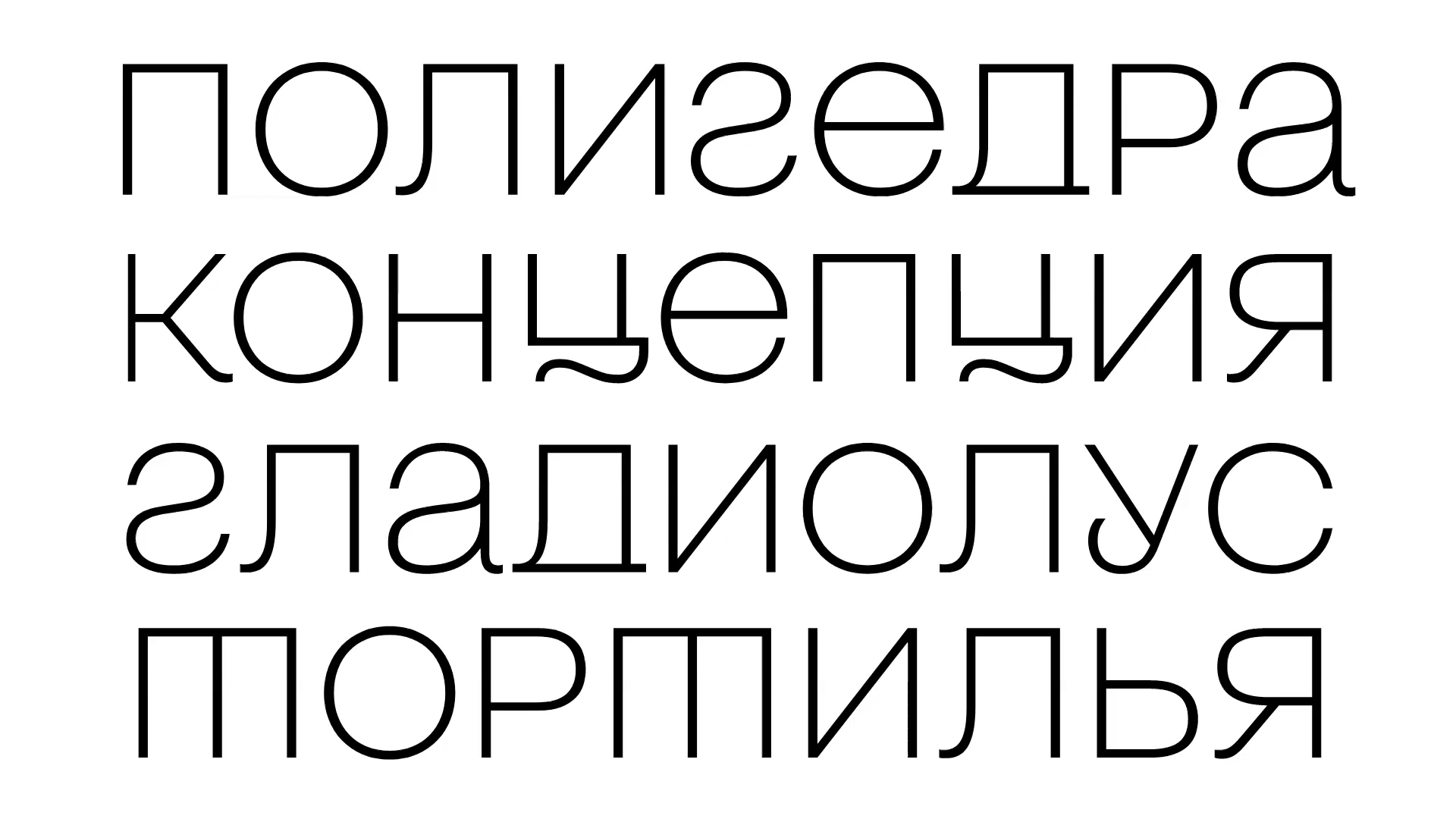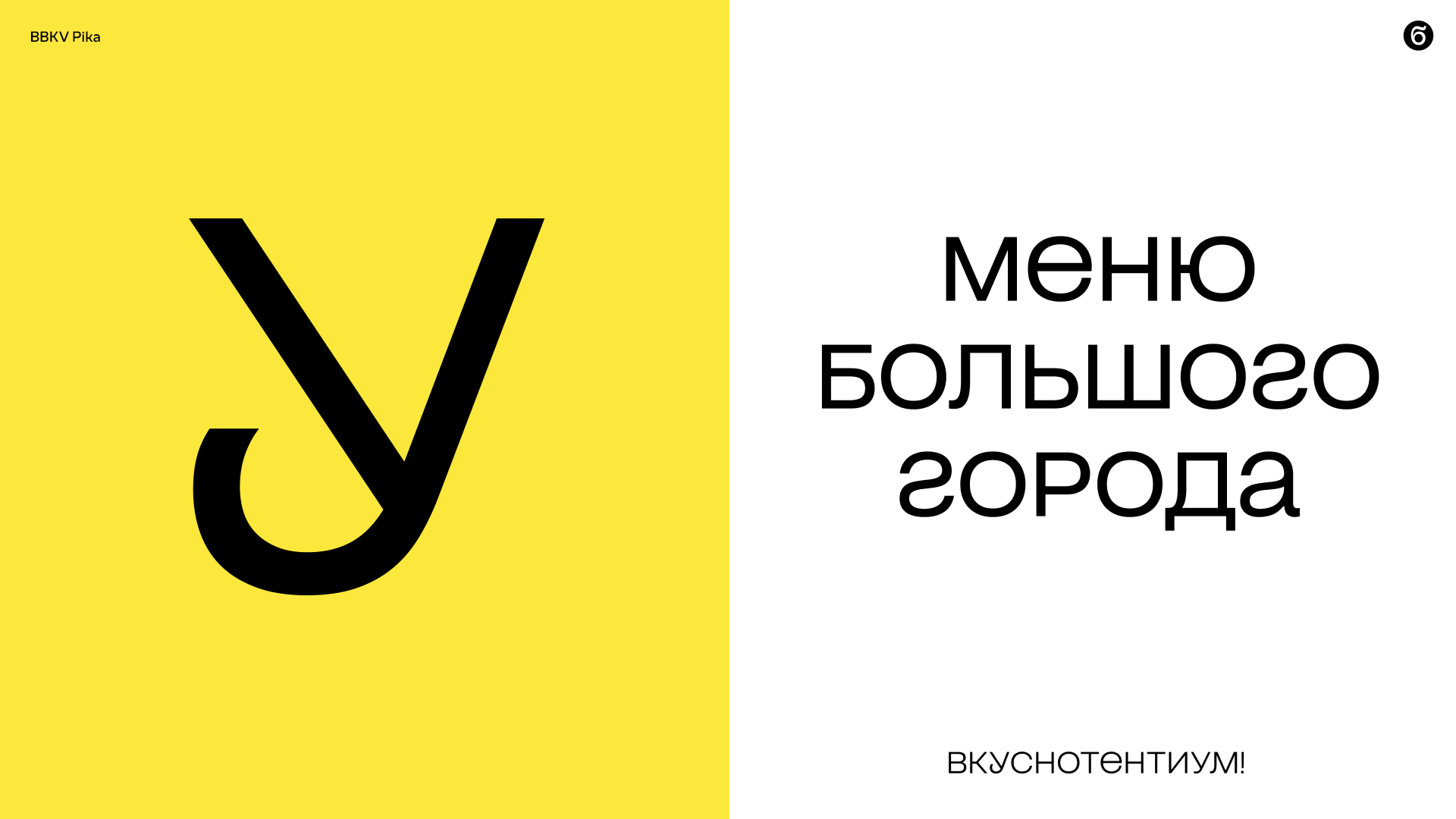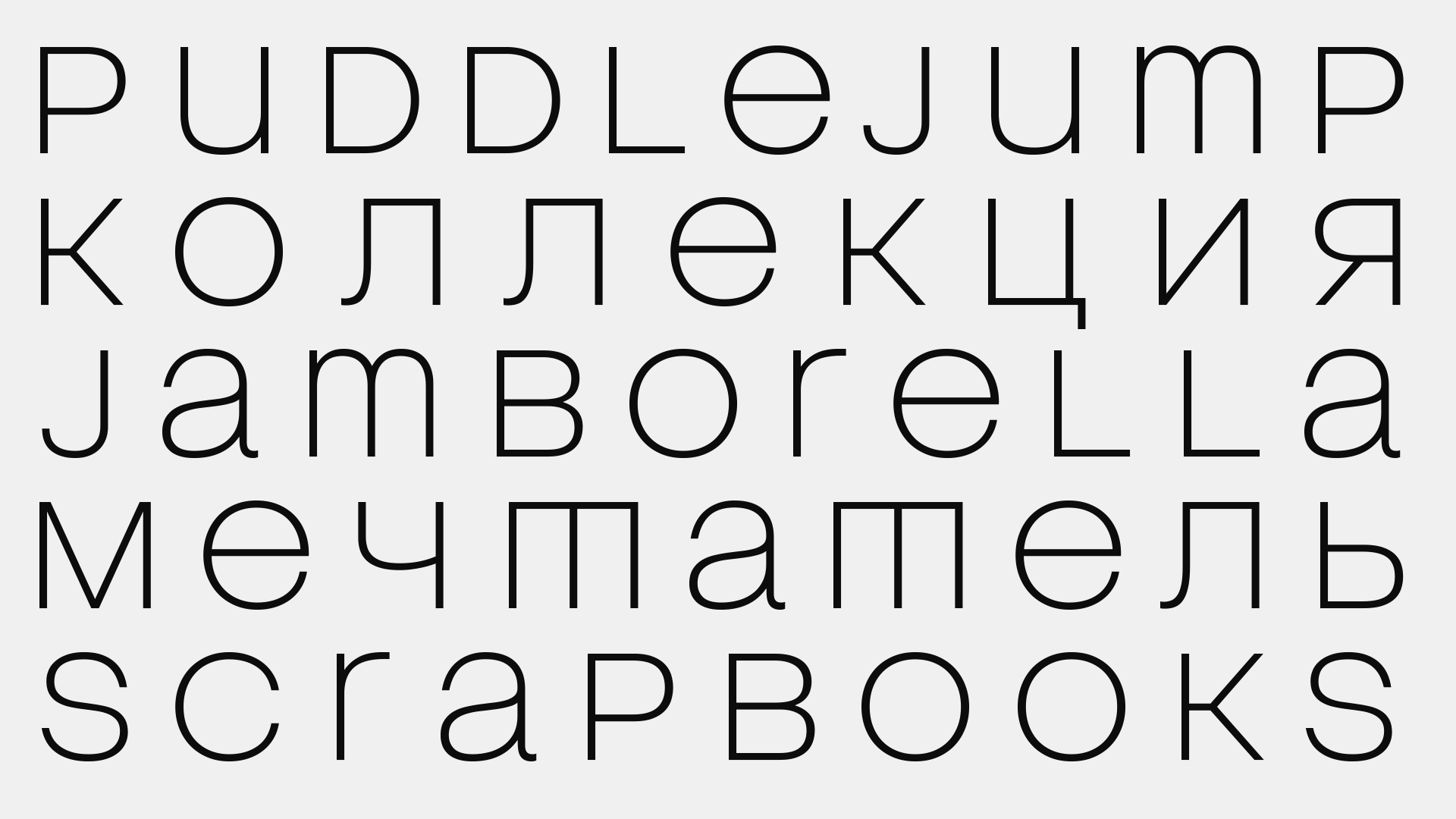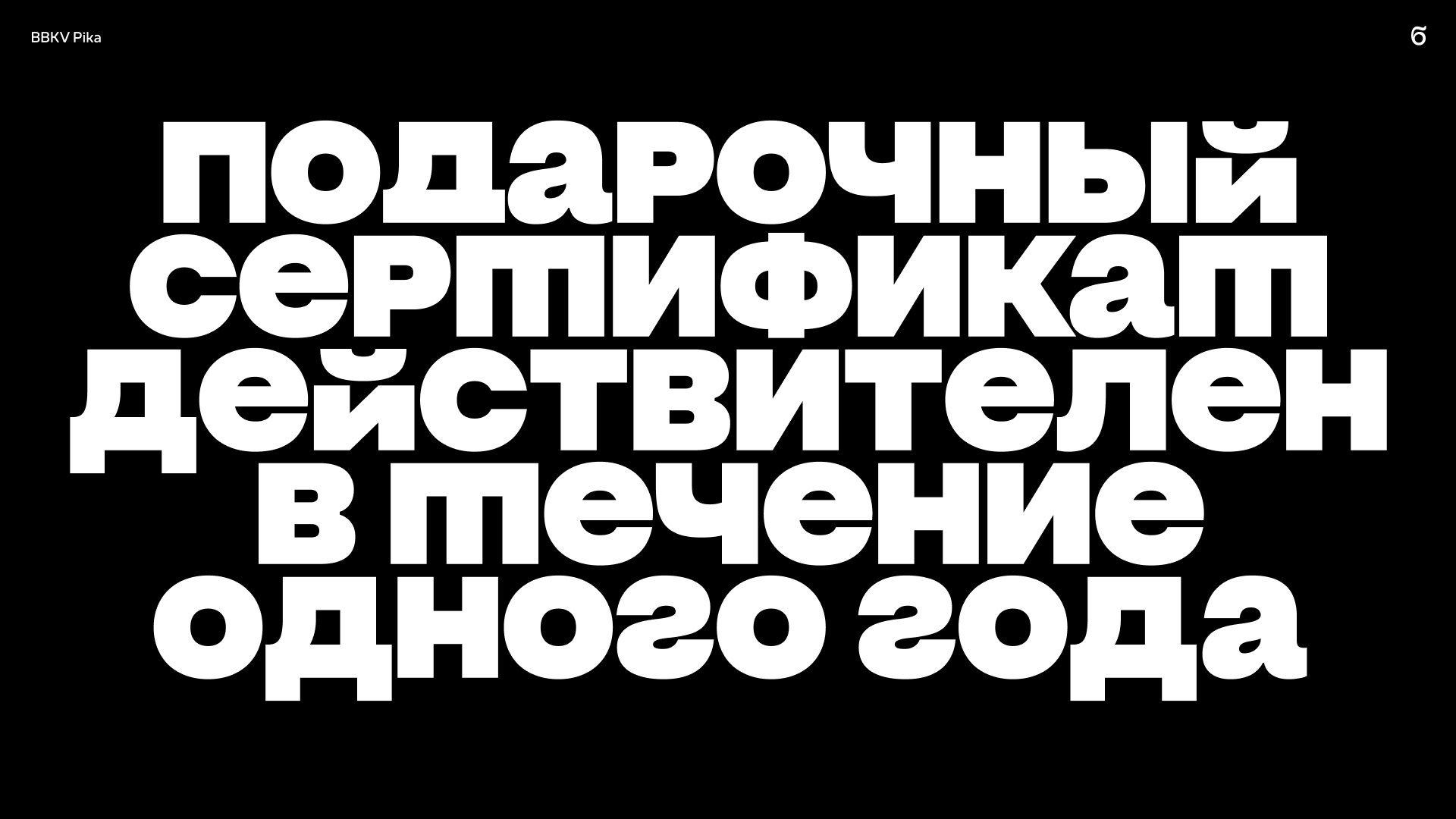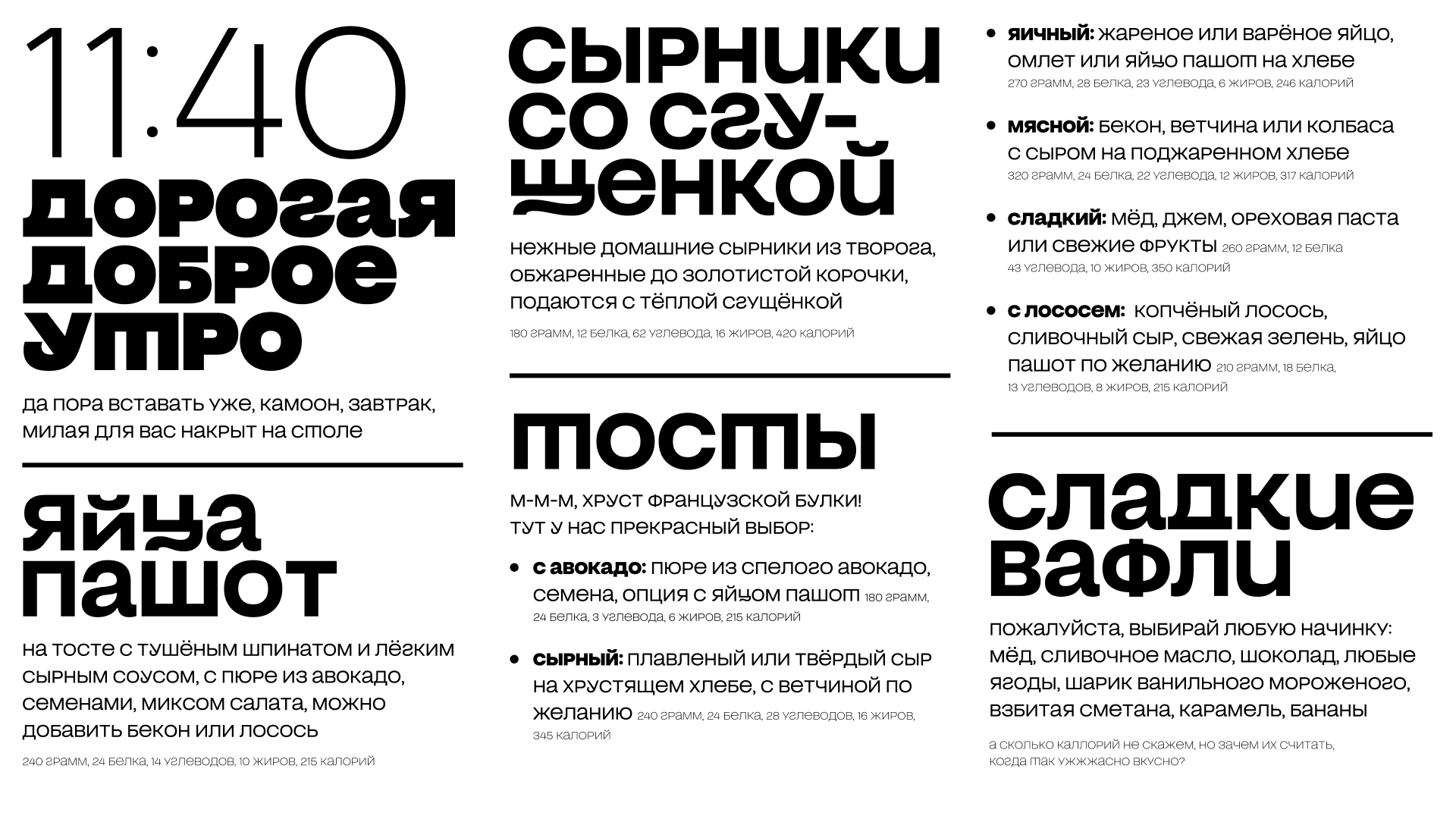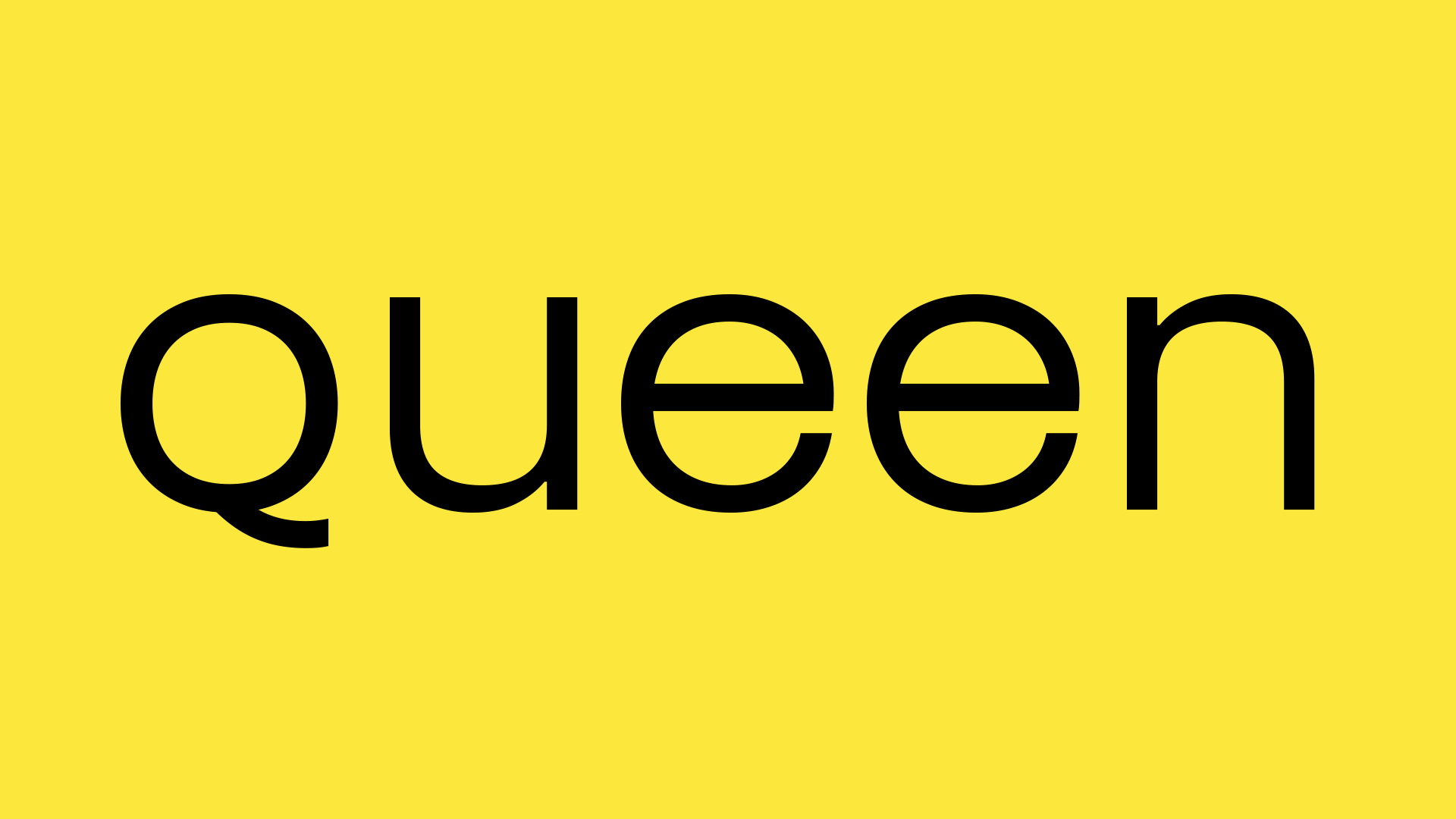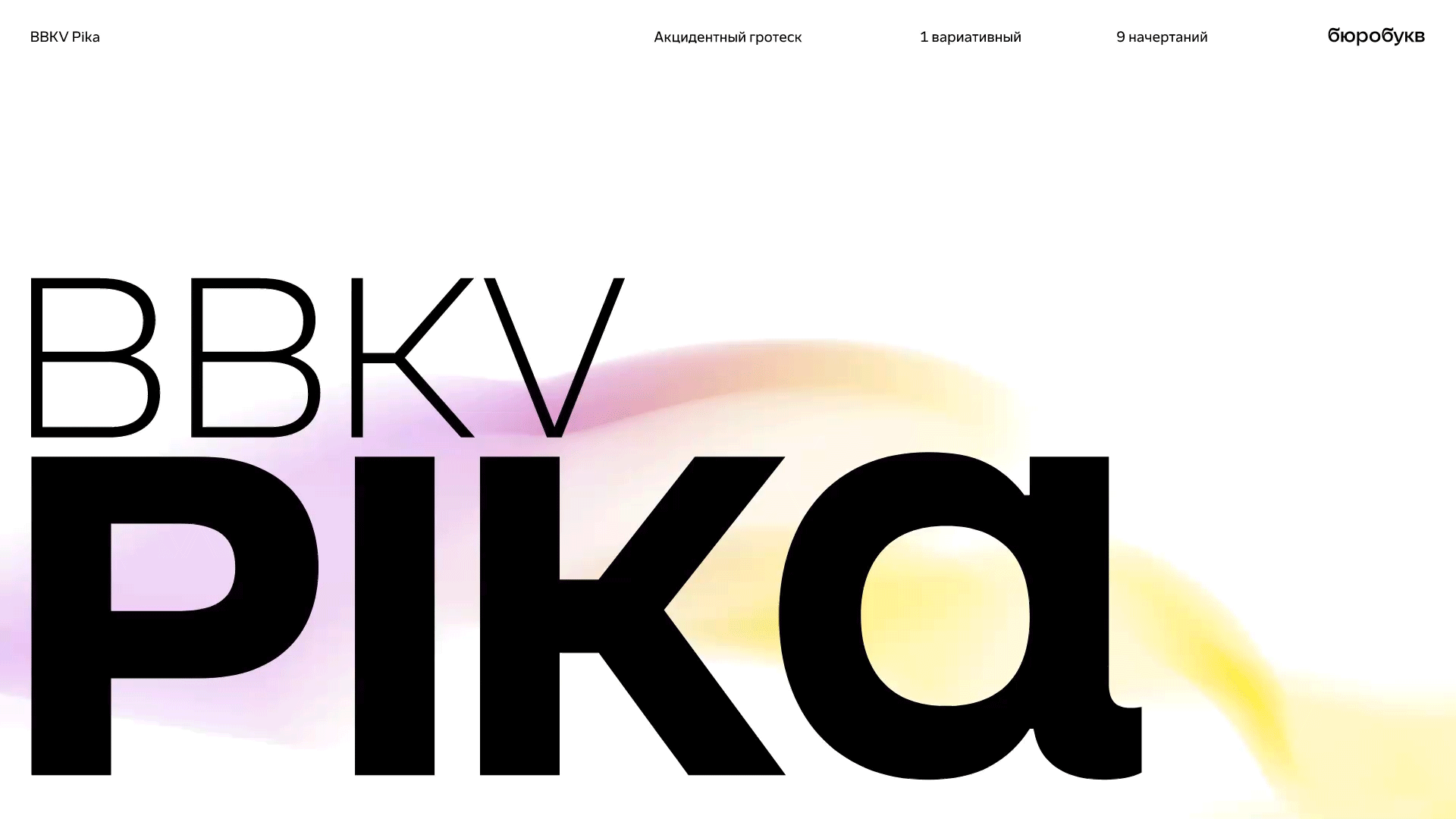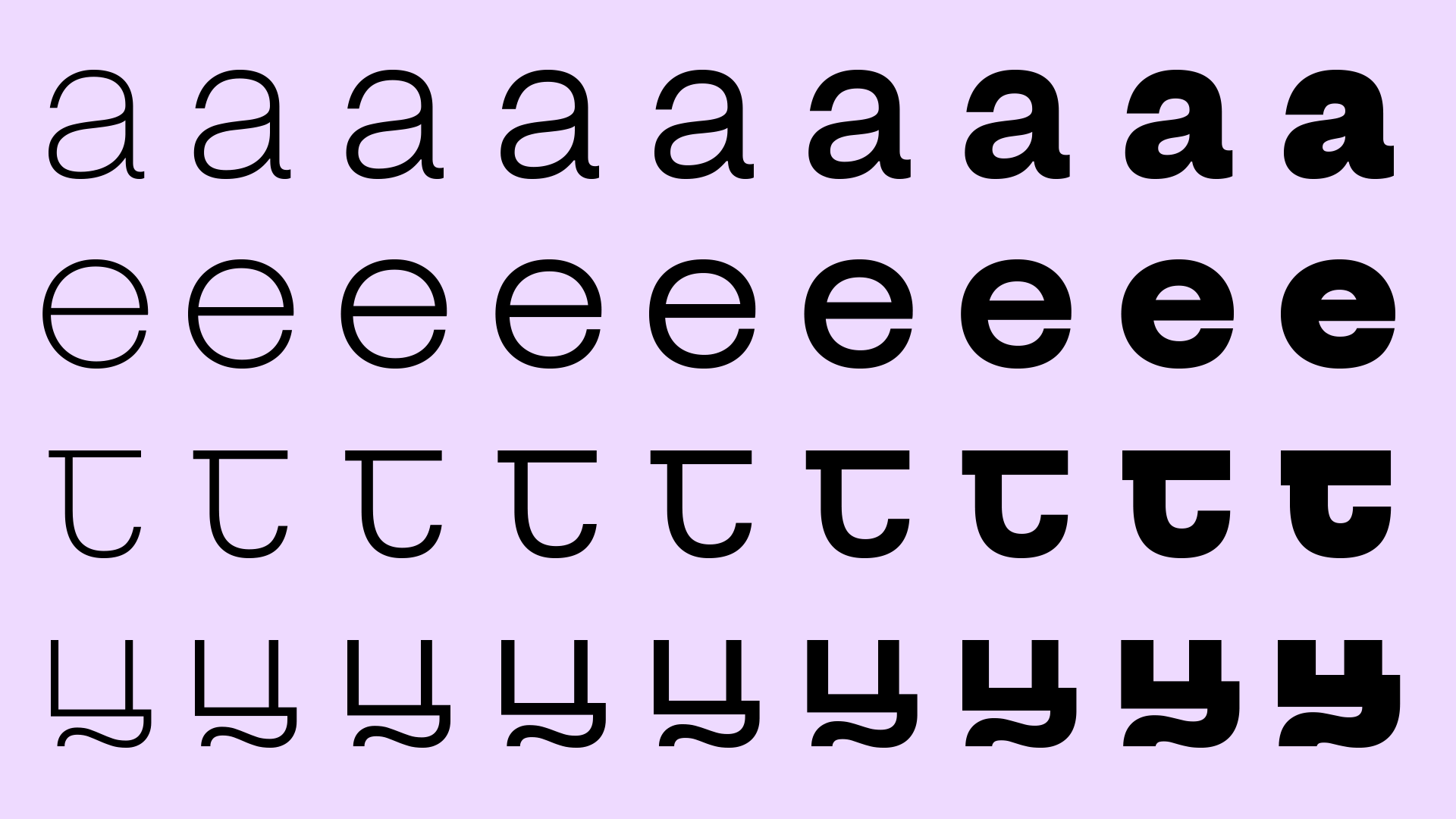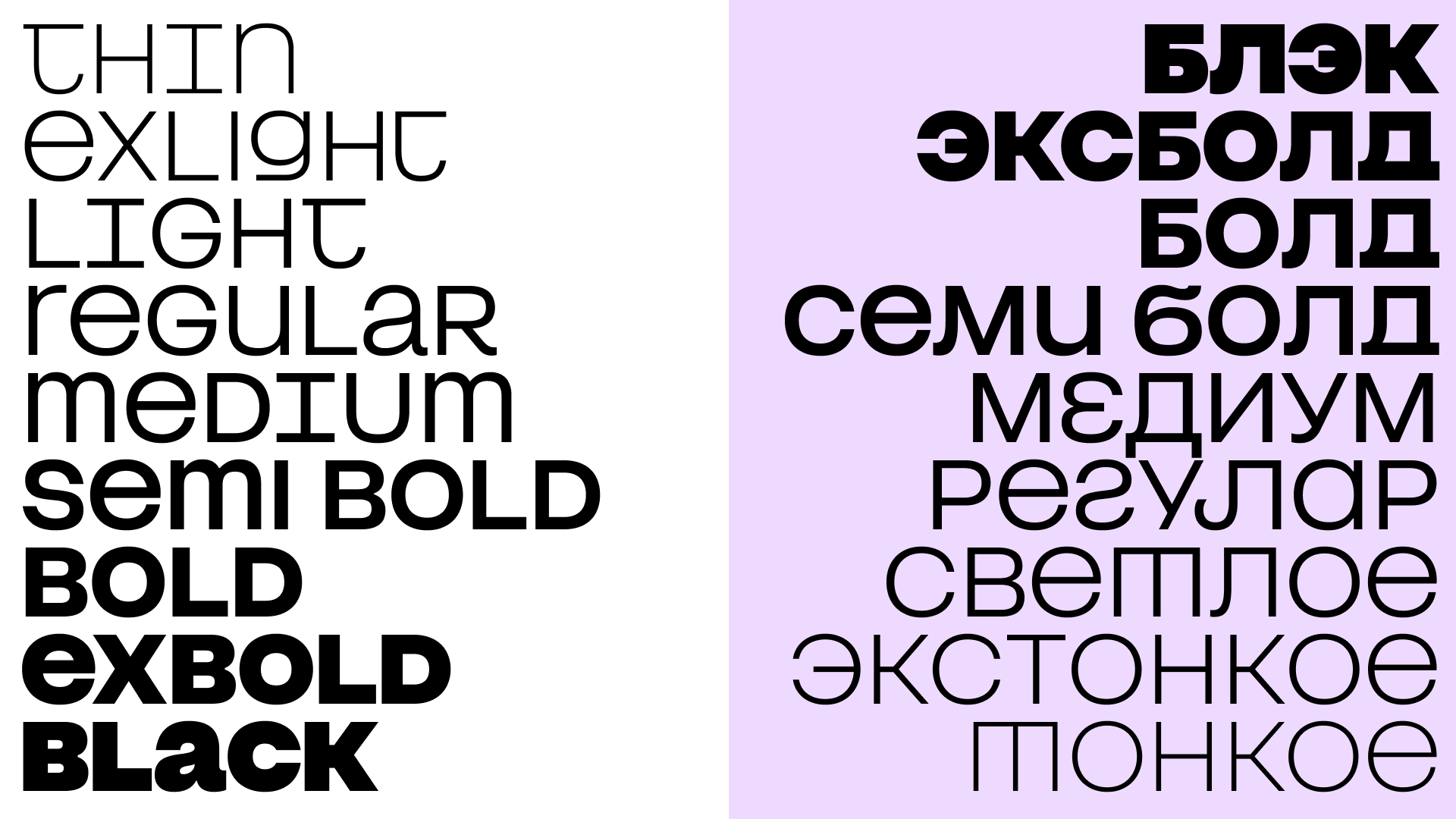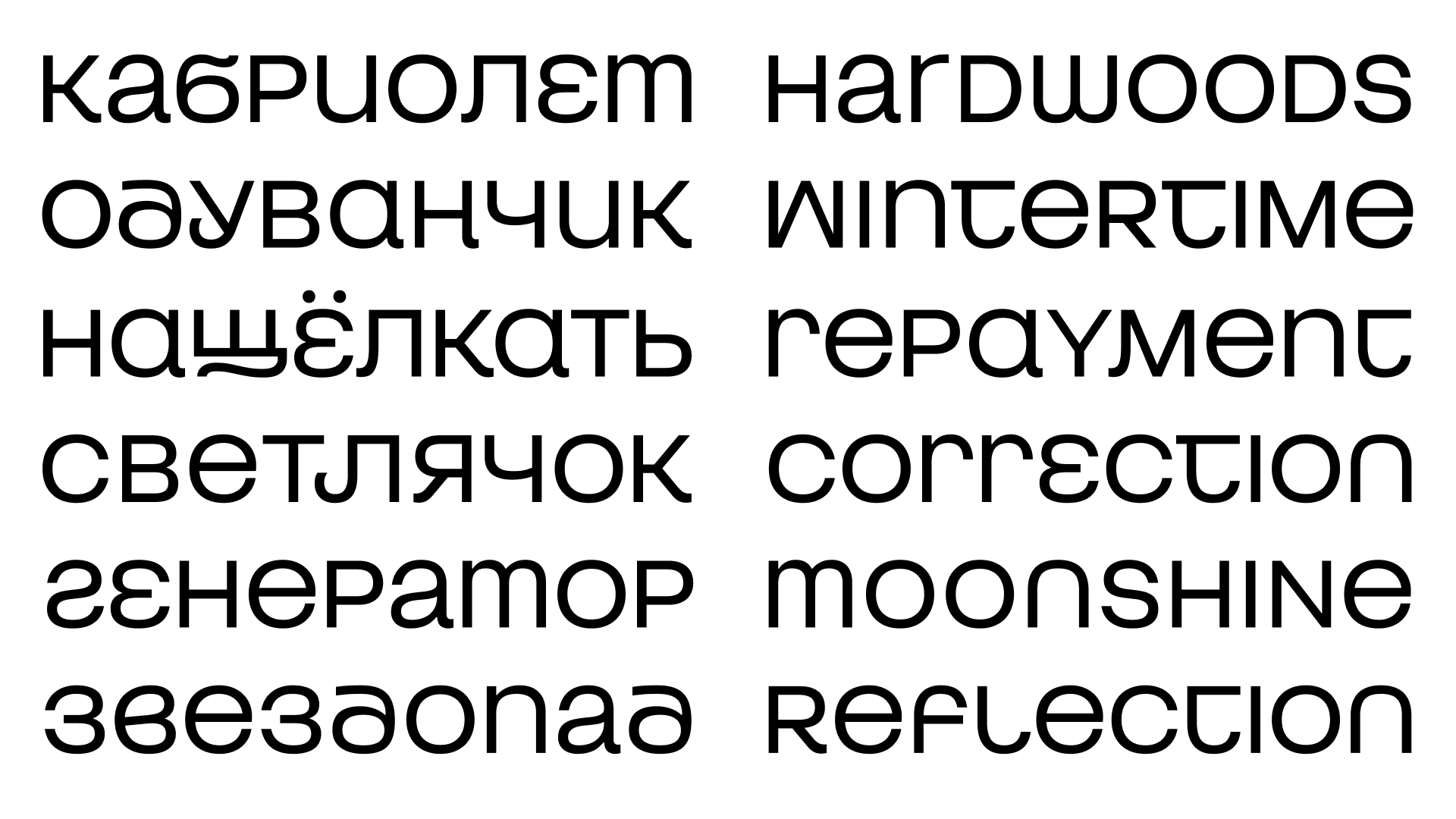
BBKV Pika
Pika — шрифт, название которого отсылает к японскому слову «pika» — «искра». Это эксперимент с юникейсом, который часто используется в латинице, но не в кириллице. В кириллице строчные и прописные буквы часто совпадают, и юникейс не всегда читается как намеренный приём. Но что будет, если мы добавим больше неожиданных форм? Так мы сможем добиться по-настоящему живого и выразительного результата, как в кириллице, так и в латинице.
Таня Черкиз, шрифтовой дизайнер